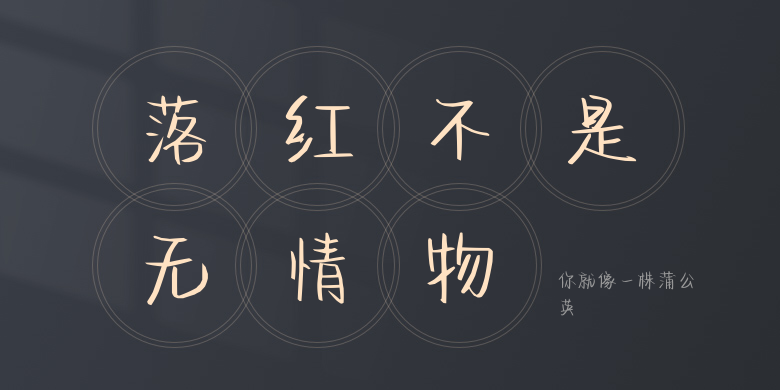
你就像一株蒲公英
你就像一株蒲公英,这款字体结构工整、笔画清晰,兼顾美观与易读性,适用于标题、正文、海报、包装、LOGO 等多种场景。字形优雅稳定,风格百搭耐看,适配日常排版与创意设计,让文字呈现更舒适、更具质感。你就像一株蒲公英一笔一画,皆是细节,以均衡的比例、流畅的线条打造舒适视觉体验,字形端正大气,风格简约现代。无论是商业设计、品牌宣传还是日常排版,都能轻松驾驭,让文字更有格调与力量。你就像一株蒲公英字体下载。